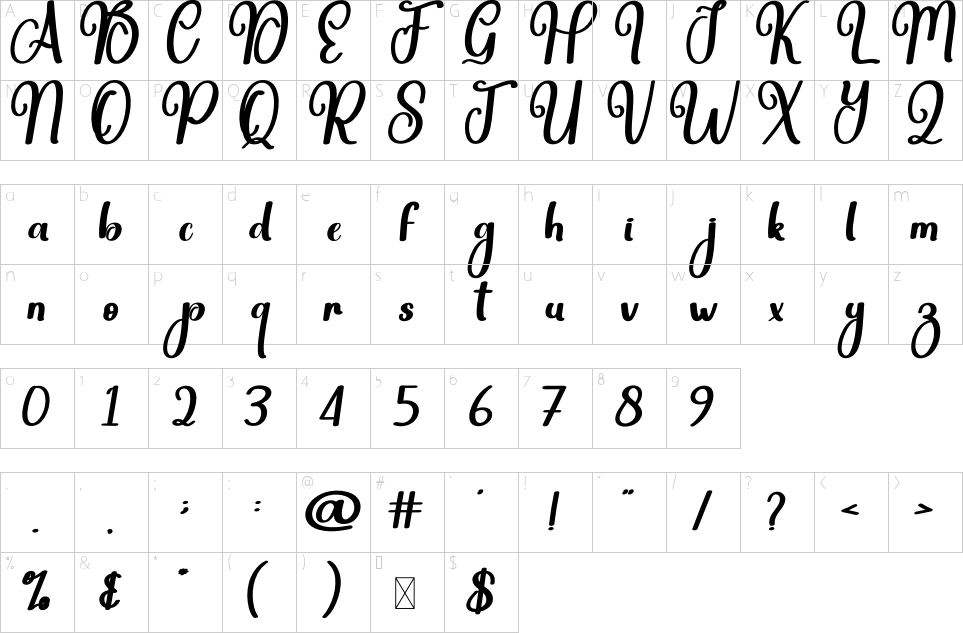
Aunty Font – Download Grátis
A fonte Aunty é uma opção gratuita e divertida para designers gráficos e amadores. Ela foi criada por William Jhordy e já foi baixada mais de mil vezes. Aunty é uma fonte de família com traços alegres e fáceis de ler, adequada para uso em design gráfico, branding e até mesmo para criar cartões de aniversário. Se você está procurando por uma fonte que seja tanto funcional quanto divertida, Aunty pode ser a opção perfeita para você. Com apenas um clique, você pode adicionar um toque especial a qualquer projeto que está trabalhando.